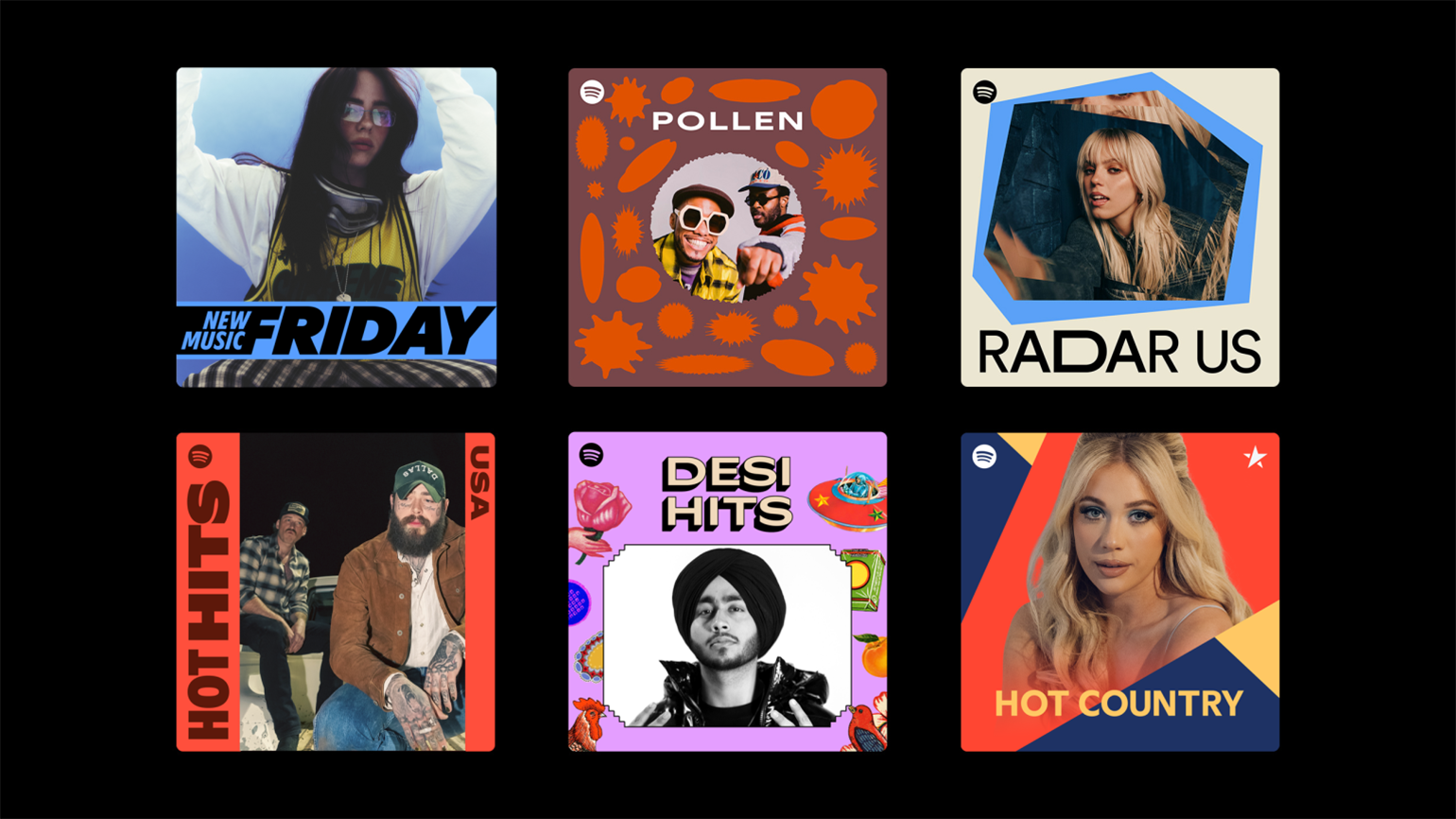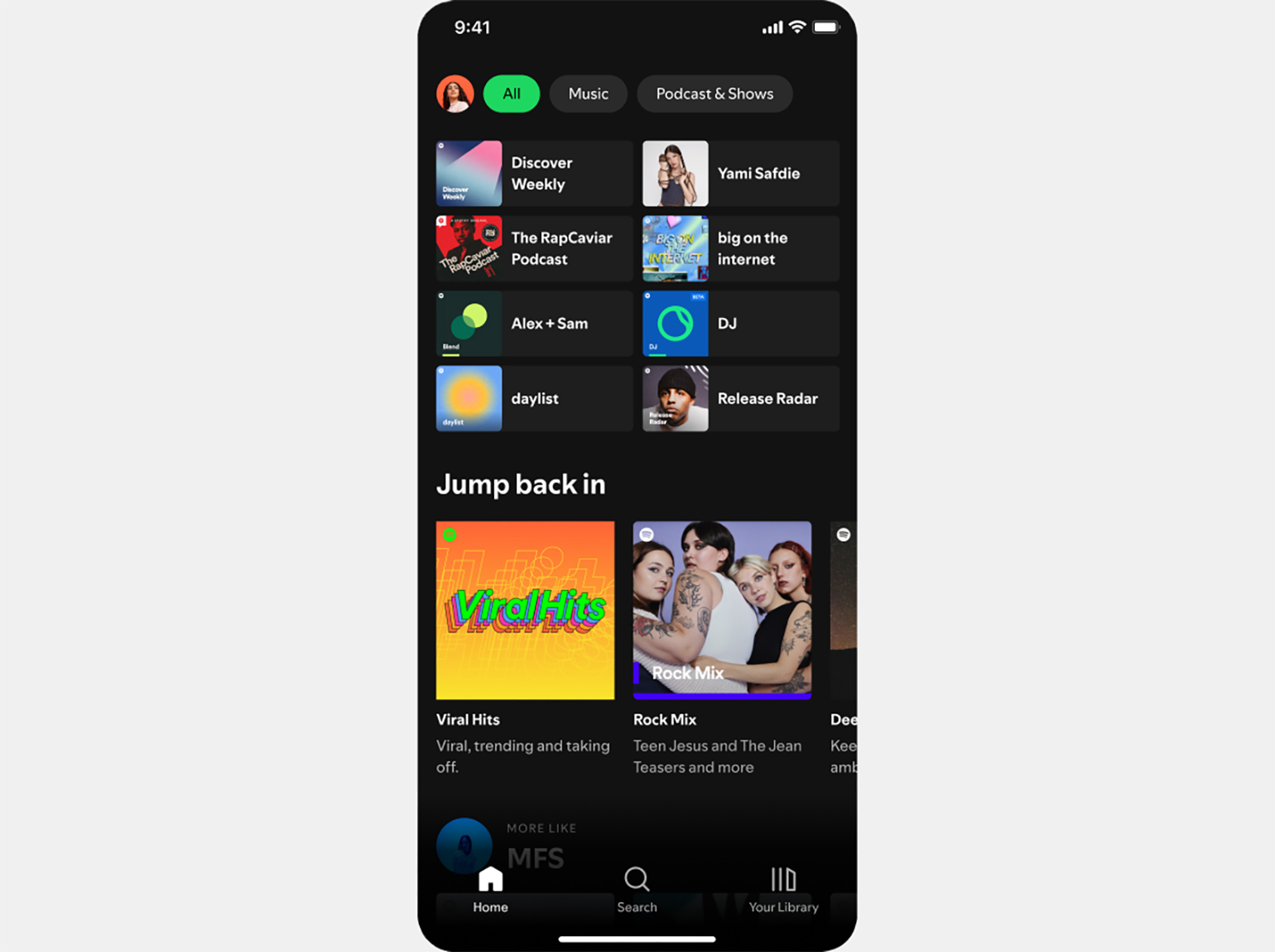
Spotify представила новый фирменный шрифт Mix
Он отражает динамичную и энергично развивающуюся аудиокультуру.
На стриминговой платформе Spotify решили заменить шрифт на вариативный и созданный специально для сервиса. Его назвали Spotify Mix: он заменит геометрический гротескный шрифт Circular в мобильных приложениях и в браузерной версии сервиса. Кроме того, новый шрифт попадёт в маркетинговые визуальные коммуникации и в оформление для мероприятий — например, Spotify Beach, которое будет проходить во время фестиваля Cannes Lions в июне.
Главная особенность нового фирменного шрифта — переменчивость. Как рассказал руководитель международного отдела бренд-дизайна Spotify Расмус Вэнгелин, чтобы его создать, они отказались от традиционных ограничений типографического мастерства и соединили вместе элементы различных шрифтовых стилей.
В результате получился шрифт без засечек, в котором есть черты как классики, так и современности. В графике угадывается форма звуковых волн, которая вызывает ощущение ритма. Сочетание острых углов и плавных изгибов придаёт шрифту тот особый характер, который визуально отражает суть платформы Spotify.
Spotify Mix компания создала в сотрудничестве с берлинской шрифтовой студией Dinamo. Этот шрифт будет использоваться при оформлении всего текстового контента, который написан на языках с латиницей. Кириллической версии Spotify Mix пока не существует.